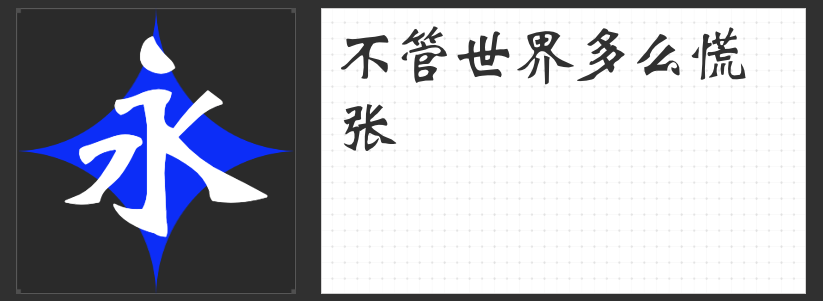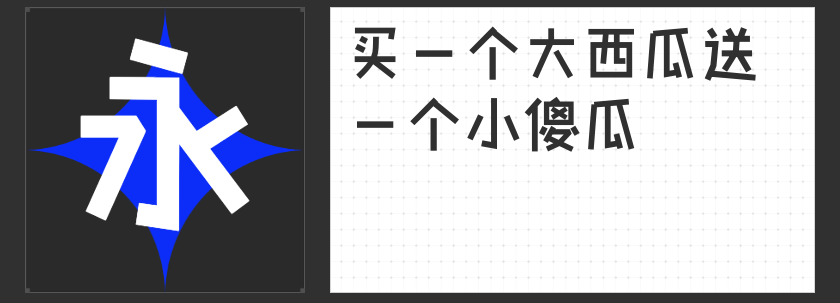
用字形美学唤醒品牌魅力·四款高质感包装设计字体推荐
在包装设计中,字体是品牌与消费者对话的第一语言。一款契合产品调性的字体,既能强化视觉记忆,又能传递品牌温度。本文精选四款风格鲜明的商业字体,从稚拙童趣到刚劲大气,为包装设计注入多元美学基因。
一、 励字星宜简
这款字体以“拼接感”为核心设计语言,厚重笔画中透出孩童涂鸦般的稚拙天真。起落笔与拐角处均采用圆角处理,柔和的线条与不规则的笔画衔接形成视觉张力,仿佛将手工剪纸的趣味融入印刷字体。适用于儿童食品、文创周边或手作品牌包装,其天真气质能瞬间拉近与年轻消费者的距离,传递“自然无拘束”的品牌态度。
二、 励字美黑简
融合黑体的现代感与宋体的书卷气,励字美黑简以匀称的笔画与清秀的结构诠释“端正正气”的视觉美学。其横细竖粗的经典比例中暗藏细节巧思:横画末端微妙的弧度、撇捺的舒展张力,赋予字体既传统又摩登的气质。适合高端茶饮、中式糕点或文化类产品的包装设计,在传递品质感的同时,以克制的设计语言彰显品牌底蕴。
三、 字圈也字呆板黑
看似“呆板”的名字下,实则暗藏动感基因。这款字体以15°倾斜姿态打破静态平衡,饱满粗壮的线条如建筑骨架般坚实有力,拐角处的锐利转折强化视觉冲击。其稳重感与力量感并存,适合运动装备、能量饮料或男性护肤品包装,通过字形传递“可靠”“进取”的品牌价值,在货架陈列中形成强识别度。
四、 励字魏体简繁
取魏碑书法之精髓,励字魏体简繁将碑刻的刀凿痕迹转化为规整的印刷字体。点画如刀劈斧凿,收笔方圆兼施,结字紧密而不失呼吸感,既有碑刻的雄浑大气,又具现代字体的易读性。适用于酒类、茶叶或传统工艺品包装,以字形承载文化厚度,在方寸之间展现品牌的历史积淀与工艺匠心。
四款字体以不同维度诠释包装设计的可能性。它们不仅是信息载体,更是品牌精神的视觉转译。设计师可根据产品定位与目标人群,选择契合的字体语言,让包装成为无声却有力的品牌故事讲述者。